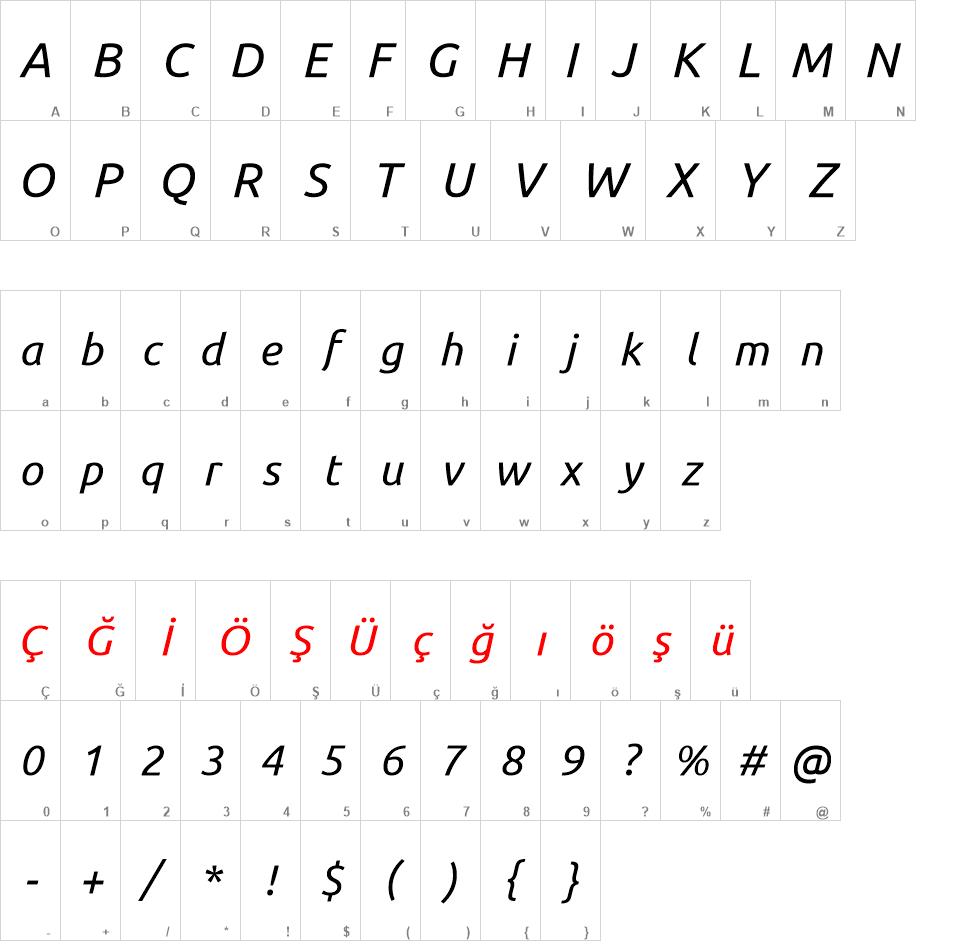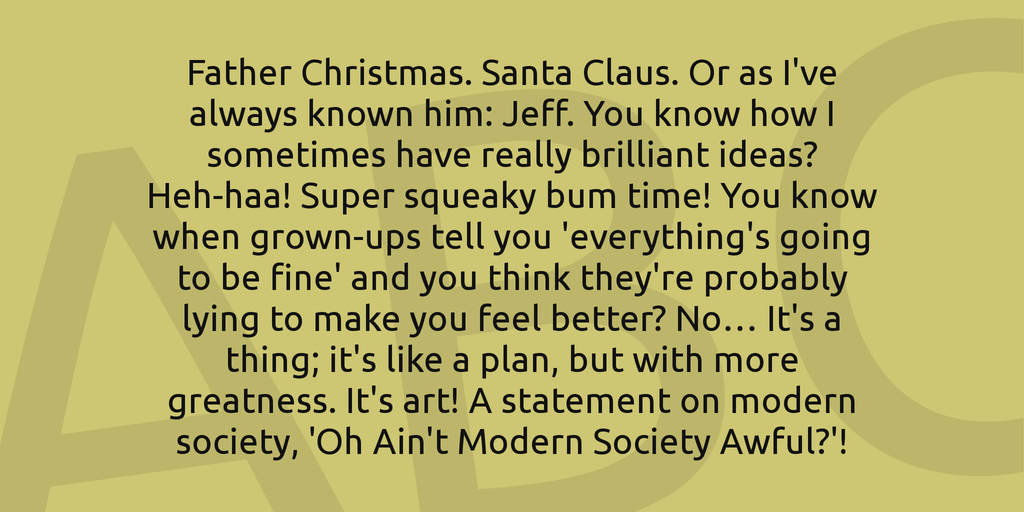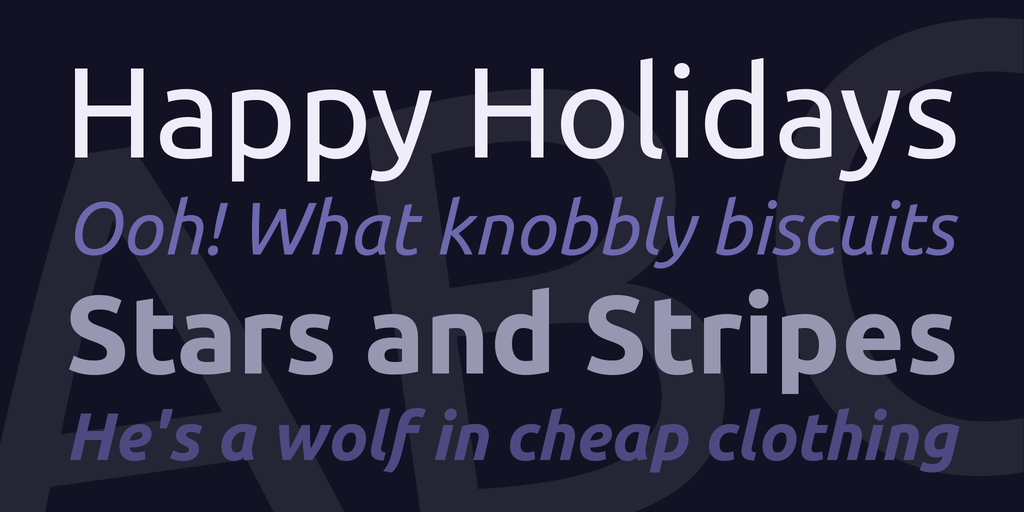
Ubuntu Font Ailesi font
Ubuntu Yazı Tipi Ailesi, yeni libre / açık yazı tipleriyle eşleşen bir takım kümelerdir. Geliştirme, daha geniş Serbest Yazılım topluluğu ve Ubuntu projesi adına Kanonik tarafından finanse edilmektedir. Teknik font tasarımı çalışmaları ve uygulaması Dalton Maag tarafından üstlenilmektedir.
Yazı tipi ailesi üretmek için kullanılan son yazı tipi TrueType / OpenType dosyaları ve tasarım dosyaları açık lisans altında dağıtılır ve açıkça deneme, değiştirme, paylaşma ve geliştirme önerilir. Yazı tipi sans-serif'tir, OpenType özelliklerini kullanır ve masaüstü ve mobil bilgi işlem ekranlarında netlik için elle ima edilir.